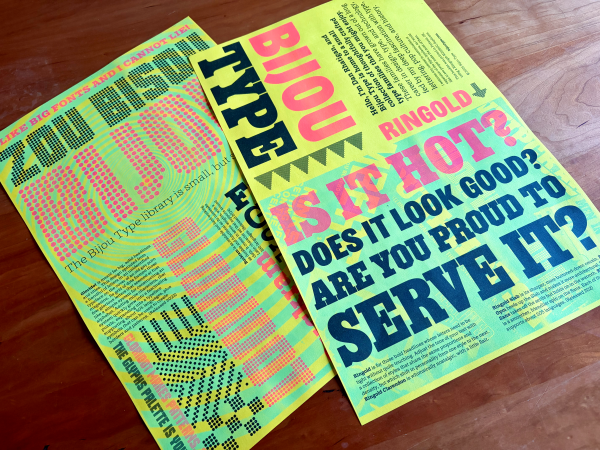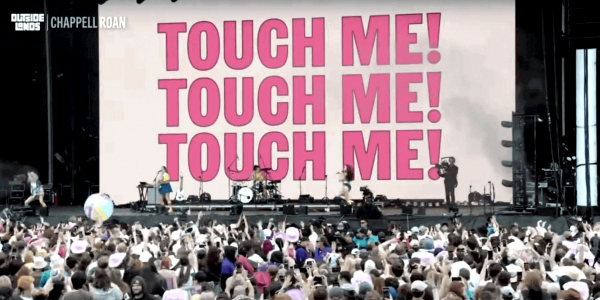
还记得去年十月蒙纳字体与品牌论坛上的 Dan Rhatigan 吗?在台上侃侃而谈的他,私下却极度社恐。他的另一面是,玩一台“脾气暴躁”的老式印刷机,还有从倒闭美术店淘回来十三箱转印字体纸。
Dan 自嘲是“字体宅(type nerd)”,但这个标签远不足以概括他:资深设计师、教育工作者、历史研究者、旧技术收藏家。
Dan 2024 年重返 Monotype,相信“对行业有利的事,才对公司有利”。
近日,我们和 Dan 进行了一场轻松又多面的对话,聊了聊他如何在社交焦虑中找到自己的节奏、为什么做了 16 年独立杂志、那些“过时”印刷技术为何让他着迷,以及职业倦怠后如何重新找到意义,相信每一位设计师都能在其中找到共鸣。
Q:你的创作灵感来源于哪里?
看到大家用我完全想不到的方式来用字体,我就特别兴奋。那种感觉既美妙又刺激,让我特别想多为这个圈子做点什么。我也很爱旅行,毕竟只有到处走走,才能看到更多有意思的东西。
巴西设计师 Cyla Costa 的海报,把字体玩出新花样的例子我还特别喜欢看人们用过时的技术玩出新花样。我认识不少还在坚持活字印刷的朋友,虽然我自己动手不多,但看他们把那些老物件玩出新高度,真的很过瘾。我家里有台脾气古怪的 Risograph(孔版印刷机)。看着这些本来该退休的机器还能吐出那么有创意的东西,挺好玩的。
Dan 自己设计的 Bijou Type 字体样本,用孔版印刷机制作。Q:你现在最投入的个人项目是?
我做了一本叫 Pink Mince 的 zine(独立小杂志),已经做了 16 年了。这是一本挺有艺术感的读物,里面有摄影、排版、故事和插画。这是我的一块自留地,想怎么玩就怎么玩。
博洛尼亚 Fruit Exhibition 独立书展上卖的《Pink Mince》各期杂志。Pink Mince 给了我一个创作的理由,让我能把艺术带到新的地方,认识新的人。做字体设计有时候挺孤独的,我又经常远程办公,所以有个东西能把我和其他艺术家、设计师连在一起,这很重要。最近我带着它去了布鲁塞尔的艺术书展,还在阿姆斯特丹的一个 zine 小组讨论会上发了言。
布鲁塞尔书展现场 © Veerle Vercauteren / KANAL-Centre Pompidouaph.那次书展特别成功!周末来了大概 2500 人,我和好多没见过我杂志的人聊得很开心,他们都挺喜欢我的作品。最让我高兴的是,一周后在阿姆斯特丹,有些在布鲁塞尔见过的人居然专门跑来参加我们那个小讨论会,特别想知道怎么开始自己的出版项目。
Q:字体设计哪里最吸引你?
我是高中做校报的时候入坑的。那会儿我也画漫画,排标题得用那种刮擦式的转印字(rub-down transfer type),或者那种样式不多的标题机。就在那时候我突然明白了:换个字体,整个意思的感觉就变了。 从那以后我就迷上了。
字体设计其实特别主观,它看着就是个抽象符号,但它能很强势地决定沟通的质感。这成了平面设计里我最感兴趣的部分。字体和设计,既是我做艺术的工具,也是我看世界的方式。
Q:要你选一款最爱的字体,你选哪个?
现在的话,我得说我自己的 Bijou 字体家族。毕竟我跟它们相处的时间最长,熟悉这款字体的细枝末节。
2024 年 Amazon Music Outside Lands 音乐节直播,用的是 Bijou 家族里的 Ringold Sans 字体。来源:Amazon Music 官方直播截图。对我来说,做字体的灵感往往来自于搞清楚手头的工具做不到什么,然后去做点东西来填这个空白。
Q:有什么创意体验是你觉得大家都该试试的?
我特别推崇意大利的 Tipoteca Italiana 印刷博物馆。每年夏天,我都会和几个朋友在那儿搞一个创意驻留项目。
我们把设计师和印刷师聚在一起,逛图书馆、去威尼斯转转,在工作坊里动手玩那些历史素材。通过“玩”来接触和吸收字体历史,这种方式特别爽快,有点像是把我平时观察世界、做东西的过程浓缩了一下。
驻留项目的成员们在 Tipoteca Italiana 看作品。另外,我觉得大家都该去本地的 zine 书展逛逛。那里全是纯粹因为喜欢而创作的人,他们做作品就是因为想做。你会看到学生、年轻的职场人和各种人做出来的东西,完全不按主流出版那套来。那种地方才最有意思。
Q:你有什么特别的收藏爱好吗?
我收了一大堆 Letraset 干式转印字体纸,这以前是平面设计师的必备工具,用了几十年。电脑一来,它一夜之间就从“到处都是”变成了“古董”。现在只有少数艺术家还在用,比如 Chris Ashworth。
Letraset 及其他品牌的干式转印字体样本。我最开始收这些是为了研究做 zine 的技法。结果有一次,我从一家倒闭的画材店买了整整十三箱库存,从那以后就停不下来了。我会拿它给学生上课,也会卖给那些想做复古玩意的人,比如修老音响上的字,或者做磁带封面什么的。
除了自己用和卖的,我现在想凑齐一套完整的,每种字体、每个尺寸都要有完美品相的,然后捐给旧金山的字形档案馆。既然已经入了这个坑了,干脆就做到底吧。
Q:你和 Monotype 是怎么结缘的?
说来话长。我第一次来 Monotype 是 2008 年,当时是从雷丁大学派过来的研究员,研究非拉丁字体。后来我也做设计,跟着 Robin Nicholas 学,最后接了他的班当了英国办公室的字体总监。2015 年我觉得有点累了,就离职了,结果 2024 年又回来了。
回来的契机挺有意思。当时我在马萨诸塞州的一个印刷博物馆做研究,正好碰上 Monotype 的高管团队在那儿开会。我不小心遇到了 CEO Ninan,大家就聊起来了。感觉公司变化挺大的,好像是个回来做点事的好时机。
我现在刚接手创意服务团队的新职位。一年半前刚回来那会儿,我主要负责管理字库,看看整个库里缺什么,怎么补上,还有策划字体合集。
Q:这份工作你最喜欢哪一点?
能直接跟客户打交道的感觉还是很好的。在创意服务部门,我可以帮字体创作者找新机会。我也还在跟外面的字库厂商合作,这本来就是我爱干的事。现在的 Monotype 比我第一次来的时候视野开阔多了。
CEO Ninan 说过一句话我一直记着:“只有对整个行业有好处的事,才真正对 Monotype 有好处。”
2025 年 2 月,Dan、Candice Smith 和 Romeo Ruz 在泰国曼谷参加 BITS 品牌识别与字体研讨会。这个思路的转变挺重要的。我是真喜欢字体,希望能把这份热情传给更多人。我现在这个位置,确实让我能去传播字体的价值。我也很喜欢这份工作,特别是在 Monotype 工作,带来的出差机会。我挺幸运的,工作总能把我带到有意思的地方,见到有意思的人。
Q:说点大家不知道的,关于你的事?
我其实特别内向。大家看我能做演讲、能带项目,以为我挺外向的。但其实社交真的会把我掏空。去鸡尾酒会应酬?我简直快要恐慌发作了。如果我在会上发言,那整段时间我基本上都在“超频运转”。完了之后我得一个人静很久才能缓过来。
2024 年 12 月,Dan 在巴西圣保罗 DiaTipo 大会上做演讲。我觉得这些年跟我一起工作的销售同事应该都懂了:咱们一起出差的时候,虽然邀请我去酒会饭局会让我觉得不被落单,但其实不用真的给我留位子。
Q:不出差的时候,你住在哪儿?
在纽约那种转不开身的小单间里熬过疫情之后,我得找个大点的地方,还得有点绿色。我就搬去了俄勒冈州的波特兰,那儿气候不错,东西好吃,适合走路逛,而且我终于有了个像样的工作室。
Dan 在家,身边是 BB 和他的书。感觉就像我注定得在那儿住。我在家附近溜达,居然能碰见一群字体圈的人,有设计老师、苹果字体团队的工程师,还有以前在 Adobe 和 Extensis 工作过的。我还碰到个原来做招牌字的师傅,现在转行纹身了。我和对象交了新朋友,还养了条狗。这次搬家搬对了。